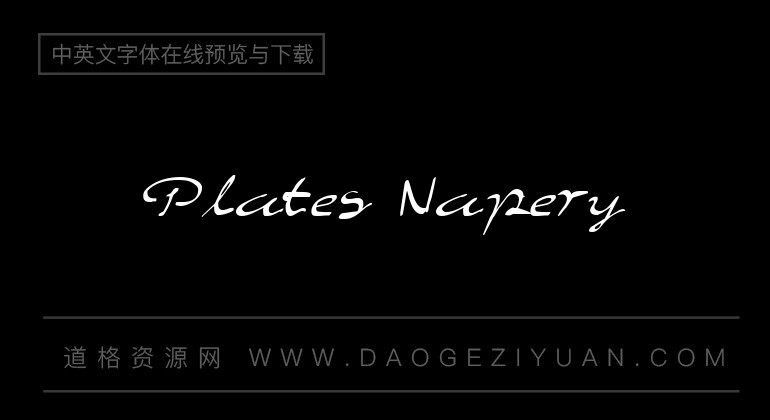
Plates Napery是一种优雅而华丽的手写字体,由设计师Alejandro Paul于2008年设计。这种字体的特点是优雅、流畅、柔和,适用于设计时需要一种精细、优美的字体风格。它具有一种典雅的氛围,适合于婚礼、餐厅、咖啡馆、设计师名片等场合使用。 Plates Napery字体采用了手写风格,具有一些类似于书法字体的特点,如笔画的弯曲和细节的精细处理。它的字形流畅优美,字母之间的连接自然流畅,让阅读者感受到一种优美的连贯性和流动感。同时,它的字母形态和线条粗细变化也非常丰富,让人感受到一种复杂而富有层次感的视觉效果。 总体来说,Plates Napery是一种非常优美、纤细、特别适合于需要体现品质、高雅和精致的场合使用的字体。内容介绍
Plates Napery是一款非常不错的手写艺术字体,具有很好的视觉感,适合于文化类的宣传设计、商业类品牌的广告和产品包装设计以及个性化文字排版等较多场景。